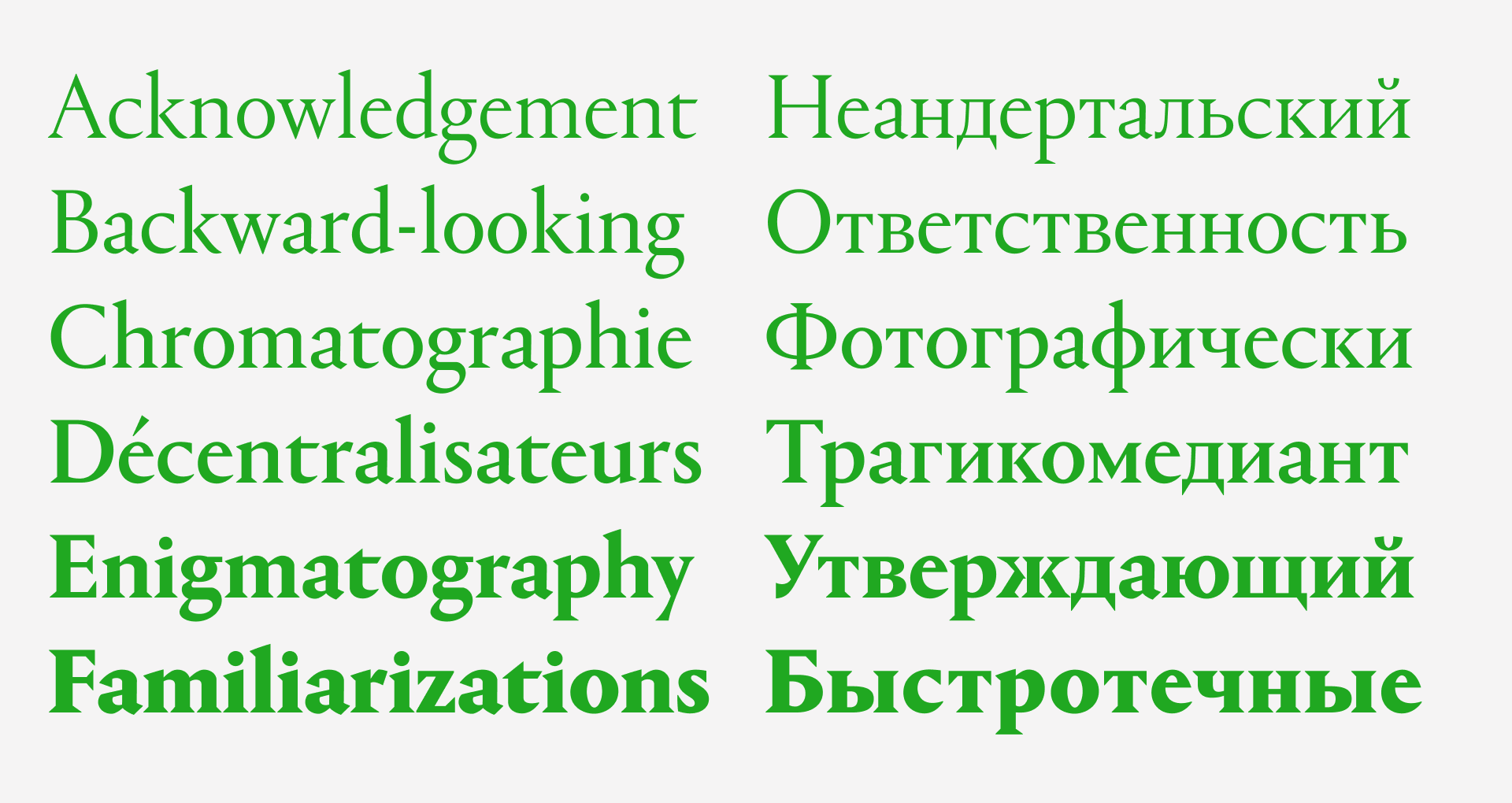
Portrait — антиква французского Возрождения, какой её видит современный и смелый дизайнер-минималист, способный добавить к ренессансным пропорциям острые треугольные засечки.
На прямые начертания Portrait повлиял шрифт Two-line Double Pica Roman Мэтра Константина (известного как Этьеннский мастер). Это была первая ренессансная антиква, вырезанная в крупном размере (32 пункта в пересчёте на современные единицы).
В италиках влияние Two-line Double Pica ощущается гораздо
Portrait Inline
Portrait Inline может показаться декоративным, но, на самом деле, именно в нём минимализм Portrait доведён до логического предела. В нём нет деталей и нюансов, присущих остальным начертаниям, а его характер определяет контраст резко сужающихся внешних штрихов с моноширинными внутренними.
Inline Sans — наследует конструкцию Inline Regular и обнажает геометрическую природу конструкций. Из-за наложения штрихов внутри знаков заголовки, набранные Inline Sans, кажутся объёмными.
Автор Portrait Бёртон Хасебе родился на Гавайях, жил в Лос-Анджелесе (где получил диплом бакалавра в Колледже искусств и дизайна Отис) и Гааге (где окончил магистратуру TypeMedia в Королевской академии художеств). Затем переехал в Нью-Йорк и с 2008-го по 2013-й работал штатным дизайнером в Commercial Type, после чего покинул эту студию и основал собственную.
Кириллицу Portrait нарисовал Илья Рудерман (CSTM Fonts).